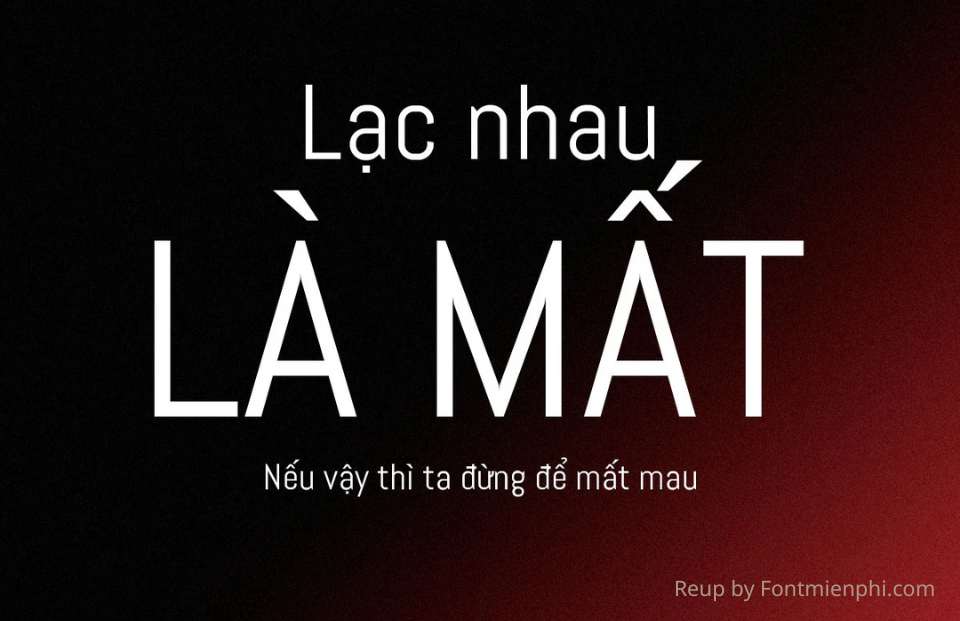
Font VL Abel Pro Regular Font Việt hoá 2026
Font VL Abel Pro Regular Việt Hóa – Giải Pháp Sans Serif Hoàn Hảo Cho Nội Dung
Trong thiết kế đồ họa và UI/UX, việc chọn font chữ cho phần nội dung (body text) luôn đòi hỏi sự khắt khe về độ “sạch”, dễ đọc và không gây mỏi mắt. Font VL Abel Pro Regular chính là một trong những ứng cử viên sáng giá nhất đáp ứng trọn vẹn các tiêu chí này.
Được Việt hóa hoàn chỉnh bởi Font Việt Linh, bộ phông chữ không chân (Sans Serif) này hứa hẹn sẽ mang đến vẻ đẹp hiện đại, tinh tế và chuyên nghiệp cho mọi dự án của bạn.
Font VL Abel Pro Regular Font Việt hoá
1. Đặc Điểm Nổi Bật Của Font VL Abel Pro Regular
Không phải ngẫu nhiên mà VL Abel Pro Regular lại được nhiều designer ưa chuộng khi dàn trang hoặc thiết kế giao diện. Bộ font này sở hữu những “điểm vàng” trong cấu trúc chữ:
Phong cách thanh mảnh, trung tính
Được thiết kế theo định dạng Regular, nét chữ của VL Abel Pro có độ dày vừa phải – không quá nặng nề như nét Bold, cũng không quá yếu ớt như nét Thin. Sự cân bằng này tạo ra một tổng thể nhẹ nhàng, thanh lịch, giúp văn bản truyền tải thông tin một cách tự nhiên nhất.
Tối ưu hóa không gian trình bày
Điểm sáng giá nhất của bộ font này nằm ở tỷ lệ chữ hơi hẹp (condensed) kết hợp cùng chiều cao ký tự (x-height) lớn. Cấu trúc này giúp các khối văn bản trông thoáng đãng, gọn gàng, đồng thời tiết kiệm tối đa diện tích hiển thị trên các thiết kế có không gian hẹp.
2. Khả Năng Ứng Dụng Linh Hoạt Trong Thiết Kế
Với ưu điểm dễ đọc và bám sát phong cách tối giản (Minimalism), Font VL Abel Pro Regular Việt hóa phát huy sức mạnh tối đa khi được sử dụng cho các đoạn văn bản dài hoặc nội dung cần sự tập trung cao. Cụ thể:
• Thiết kế UI/UX & Website: Làm font chữ mặc định cho nội dung bài viết, landing page, menu hoặc các thông báo trên ứng dụng di động.
• Ấn phẩm truyền thông: Cực kỳ phù hợp để dàn trang Brochure, Profile công ty, Catalogue giới thiệu sản phẩm.
• Sáng tạo nội dung (Content Creator): Sử dụng làm font chữ phụ đề (subtitle), mô tả chi tiết trên các bài đăng Social Media (Facebook, Instagram).
3. Bí Quyết Kết Hợp Font (Font Pairing) Hiệu Quả
Nhờ mang trong mình sắc thái trung tính, VL Abel Pro Regular là một “người bạn đồng hành” tuyệt vời khi kết hợp cùng các font chữ khác.
Để tạo ra sự tương phản thị giác hút mắt, bạn có thể sử dụng các font Serif (có chân) cổ điển hoặc các font Sans Serif nét siêu đậm (Black/Extra Bold) cho phần Tiêu đề (Heading). Lúc này, VL Abel Pro Regular sẽ đóng vai trò làm nền tảng vững chắc, giúp phần nội dung mô tả bên dưới trở nên hài hòa và dễ tiếp nhận hơn.
4. Trải Nghiệm Bản Việt Hóa Chuẩn Từ Font Việt Linh